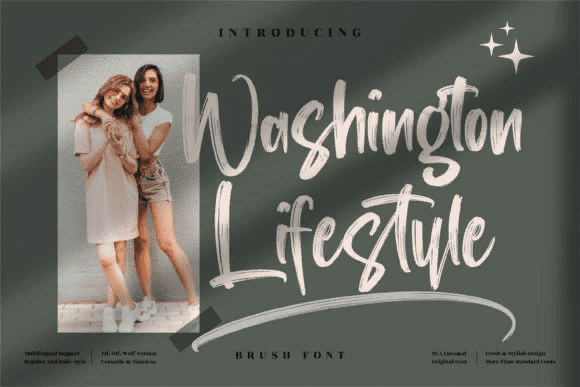
Название: Washington Lifestyle Font
Washington Lifestyle - это причудливый шрифт с матовым начертанием, выполненный в непринужденной тематике и отличающийся прекрасным стилем.
Независимо от темы, этот шрифт станет отличным дополнением к вашей библиотеке шрифтов, так как он способен приподнять любое творение.